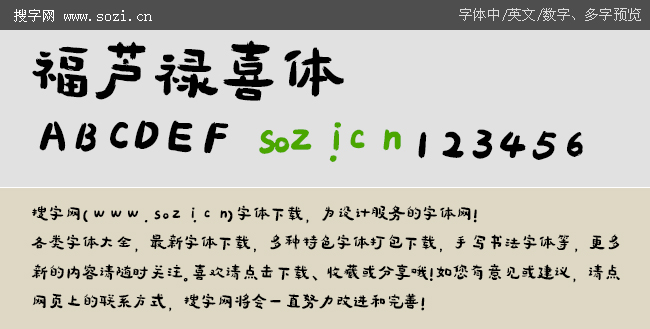
福芦禄喜体
搜字网提供一款福芦禄喜体中文字体下载, 福芦禄喜体是一款融合传统书法韵味与现代时尚审美的字体,旨在打破传统书法的规整束缚,赋予文字天真自由的视觉性格。该字体以“笔触感”为基底,通过强化毛笔书写的自然痕迹,展现墨色浓淡交织的效果。其字形结构圆润萌动,线条活泼俏皮,既传递了书法艺术的灵动之美,又适配个性化的时尚场景,实现了传统与潮流的创意碰撞。适合包装设计、海报设计、广告设计等应用。